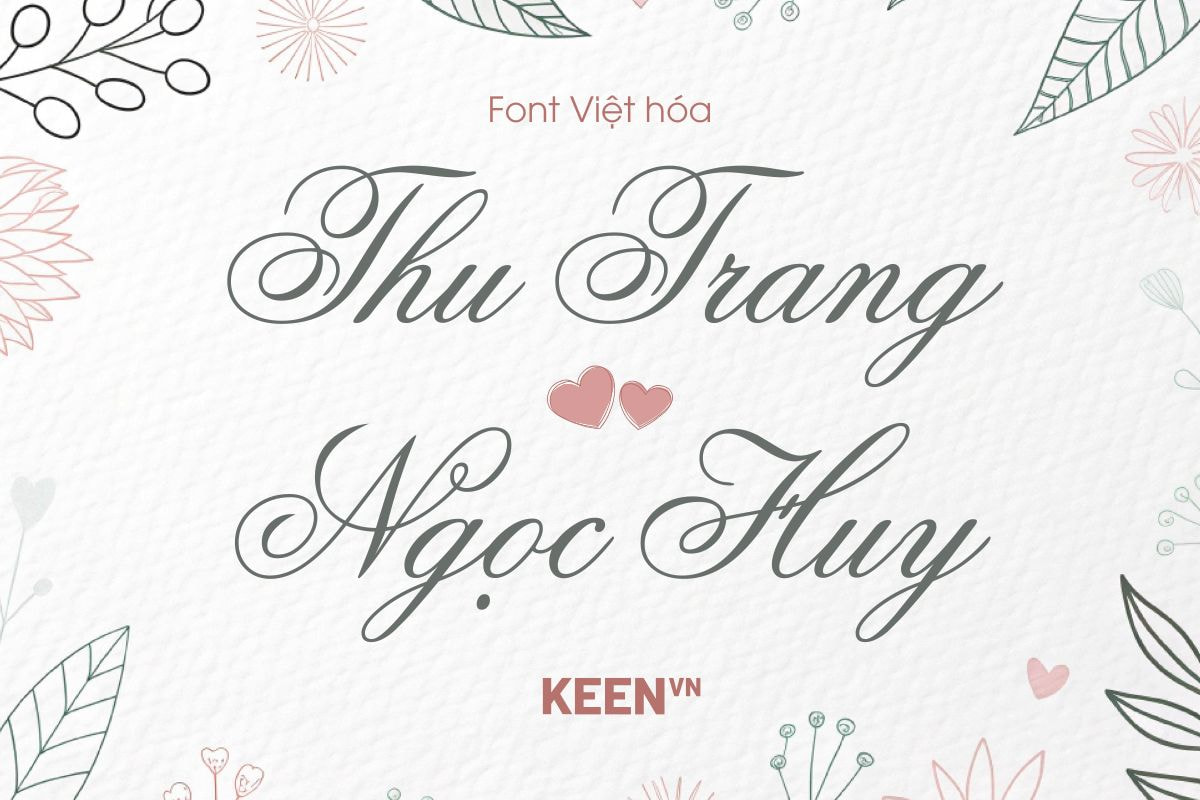
Font Việt hóa UVN Buc Thu
- Hỗ trợ đầy đủ dấu tiếng Việt
Mô tả
Font Việt Hóa UVN Buc Thu là bộ font chữ nghệ thuật với nét vẽ mềm mại, phù hợp cho thiết kế sáng tạo, in ấn, và dự án cá nhân. Với kiểu chữ độc đáo, UVN Buc Thu giúp tạo điểm nhấn cho banner, poster, thiệp mời, hoặc logo. Font hỗ trợ đầy đủ dấu tiếng Việt, đảm bảo tính thẩm mỹ và tiện dụng trong mọi ấn phẩm.
Tại sao nên chọn UVN Buc Thu?
Thiết kế tinh tế: Nét chữ thanh thoát, phù hợp với phong cách hiện đại.
Đa dạng ứng dụng: Dùng cho đồ họa, quảng cáo, in ấn, hoặc dự án cá nhân.